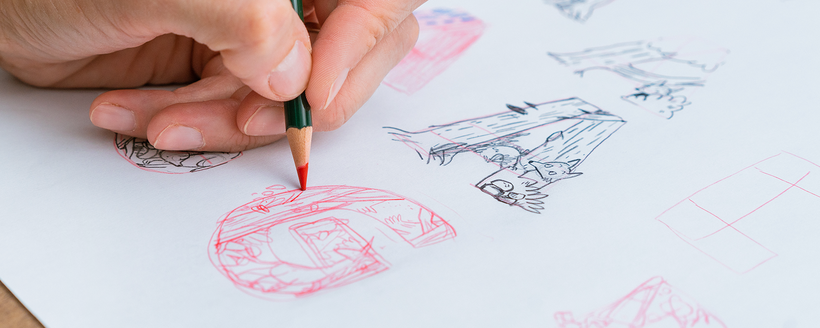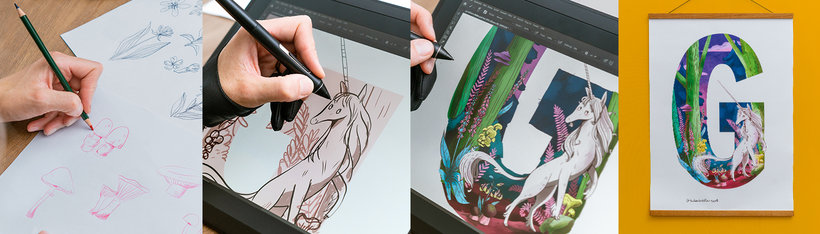
Illustrationen für Kinder: Gestalte eine dekorative Typografie
Lerne, wie du Typografie und Illustration kombinierst, um mithilfe von analogen und digitalen Techniken eine verspielte Komposition für Kinder zu gestalten
In diesem Domestika-Kurs bekommen Buchstaben einen spielerischen Charakter und werden zum Spielplatz für deine Fantasie und Zeichnungen. Mithilfe von Photoshop/Procreate kreierst du ein einzigartiges Kinderzimmer-Poster mit illustrierten Buchstaben, Wörtern oder dem gesamten Alphabet. Lasse deiner Fantasie freien Lauf und spiele mit Typografie, Illustrationen und digitalen Elementen.
Zu Beginn stellt Julia ihren Schaffensprozess, ihre Inspirationen, künstlerischen Einflüsse und ihre Werke vor. Sie zeigt dir sämtliche Arbeitsschritte, von der Idee, über erste Skizzen bis hin zur Arbeit in Photoshop und dem fertigen Poster.
Zusammen mit Julia entwickelst du anschließend ein thematisches Konzept, wählst ein Thema, Buchstaben und ein Format aus und erstellst ein Moodboard mit deinen Inspirationen. Mithilfe dieser Grundlagen entwirfst du dann deine ersten, freien Skizzen auf Papier und verwirklichst dein künstlerisches Konzept für deine ausgewählten Buchstaben und Illustrationen.
Im Anschluss hilft Julia dir, deine Skizze einzuscannen, damit du digitale Illustrationen entwerfen kannst. In Photoshop kannst du jetzt deinen Entwurf verfeinern, Details und Einzelelemente bearbeiten sowie mithilfe von Farben, Texturen und Licht- und Schatteneffekten Leben in deine Skizze bringen. Abschließend nimmst du noch letzte Korrekturen vor und platzierst die finalen Elemente deines Posters.
Zum Schluss kannst du dein Werk mit einem digitalen Wasserzeichen versehen und es entweder sofort drucken oder aus Photoshop exportieren. Außerdem gibt Julia dir einige letzte Tipps, wie du deine Arbeit anderweitig verwenden kannst und zeigt dir Wege, dich kreativ weiterzubilden.
Du erschaffst ein einzigartiges, kreatives Kinderzimmer-Poster mit illustrierten Buchstaben oder Wörtern.
Der Kurs ist für alle Fans von Typografie, Buchstaben und Illustrationen geeignet.